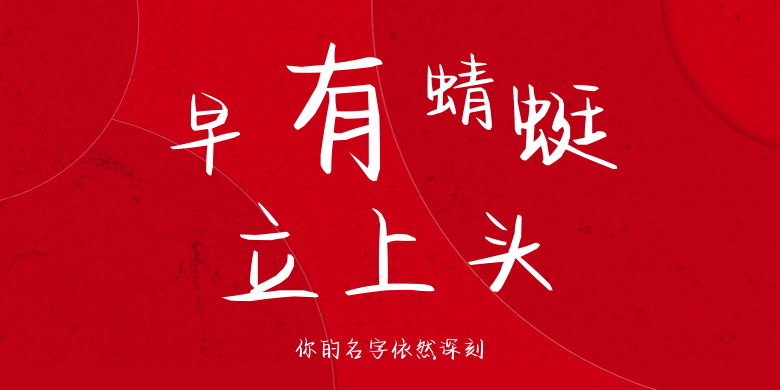
你的名字依然深刻
你的名字依然深刻,这款字体结构工整、笔画清晰,兼顾美观与易读性,适用于标题、正文、海报、包装、LOGO 等多种场景。字形优雅稳定,风格百搭耐看,适配日常排版与创意设计,让文字呈现更舒适、更具质感。你的名字依然深刻一笔一画,皆是细节,以均衡的比例、流畅的线条打造舒适视觉体验,字形端正大气,风格简约现代。无论是商业设计、品牌宣传还是日常排版,都能轻松驾驭,让文字更有格调与力量。你的名字依然深刻字体下载。